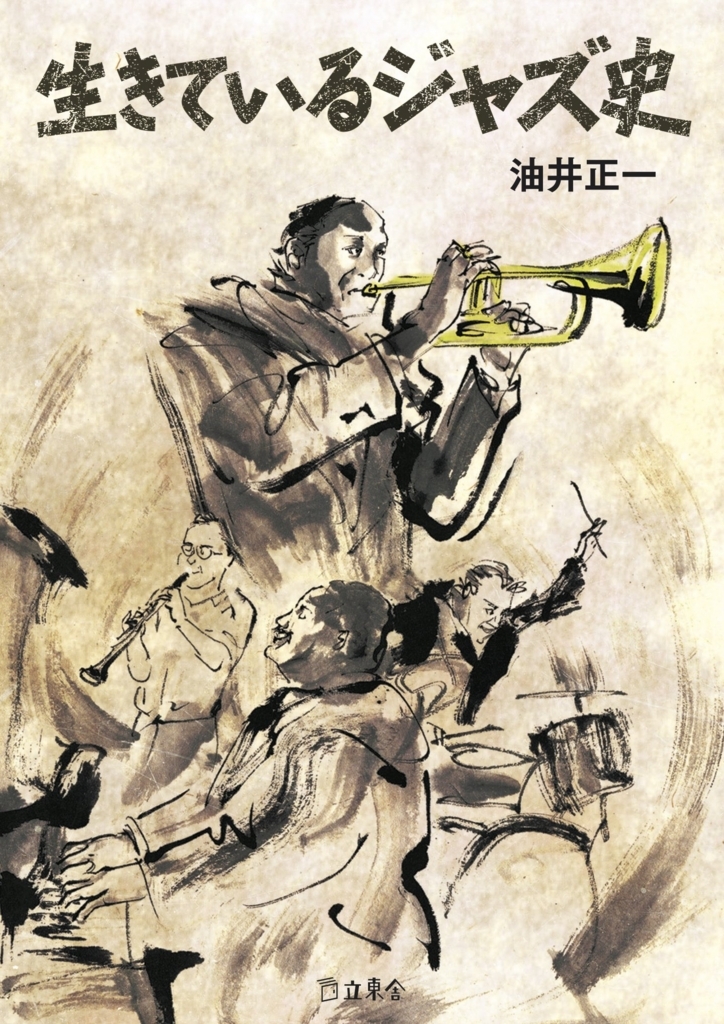
生きているジャズ史
「生きているジャズ史」は、日本のジャズ評論の第一人者と評される油井正一氏によるジャズの歴史を創世記の時代状況から有名アーティストのエピソード、様々なスタイルの栄枯盛衰、背景にある人間模様や人種問題まで語った「ジャズの歴史書」になっている。
「生きているジャズ史」のタイトルのフォントはダイナフォント角POP
立東舎文庫発行による2「生きているジャズ史」にダイナフォント 角POPが採用されている。
角POP
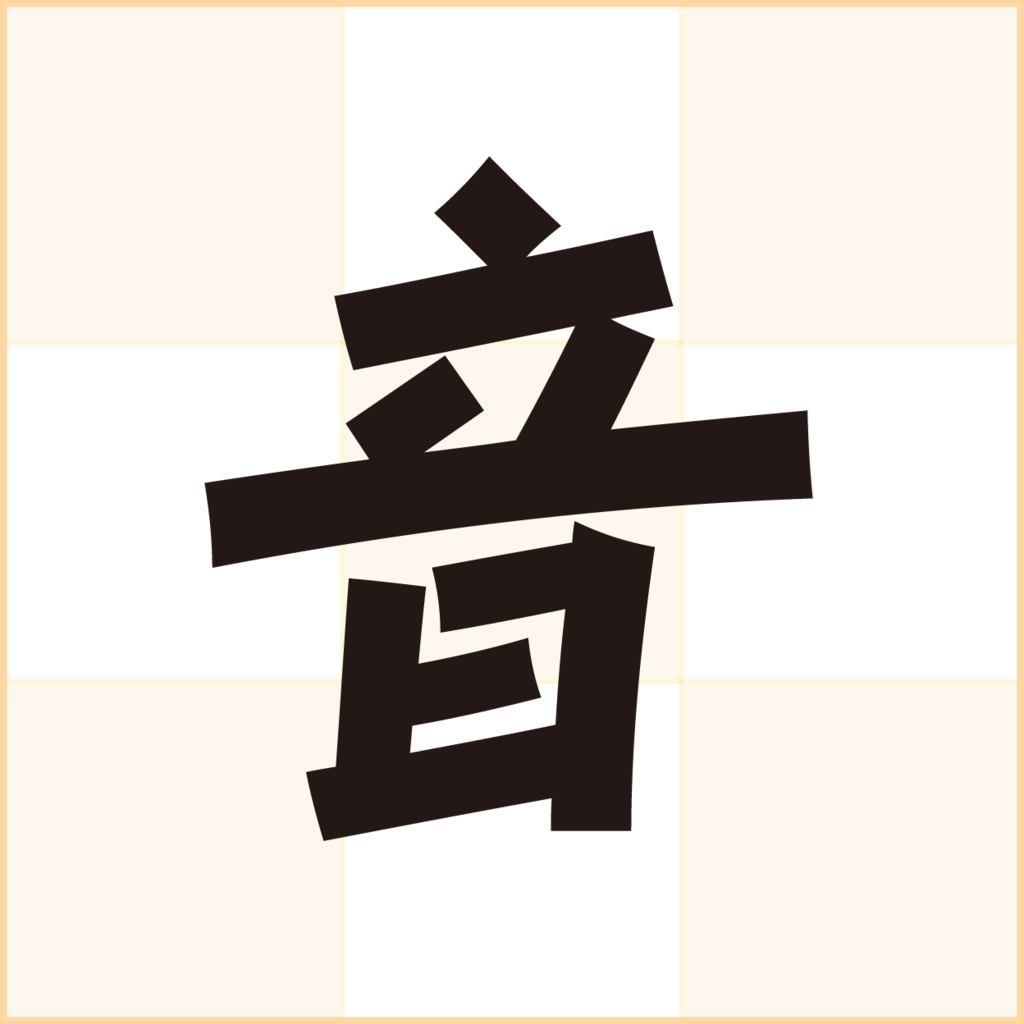
伝統楷書をベースにして、角張った字形を採用した書体。どことなくモダンな風格を備えており、タイトルやロゴといった部分での使用に適している。